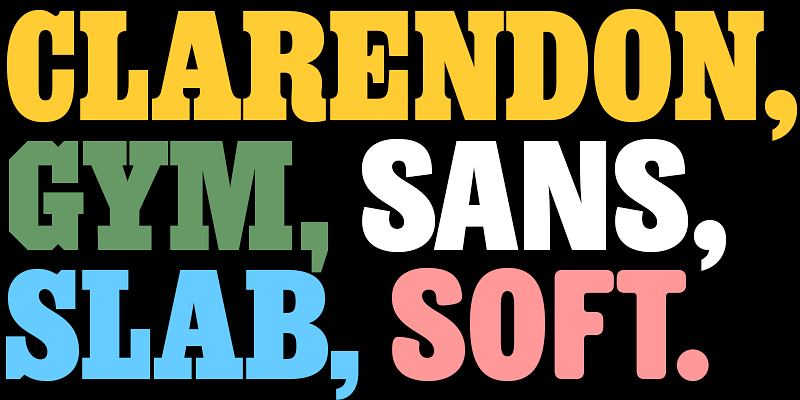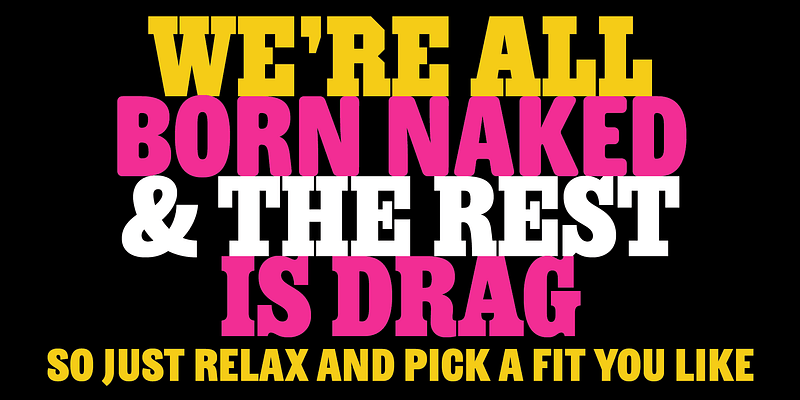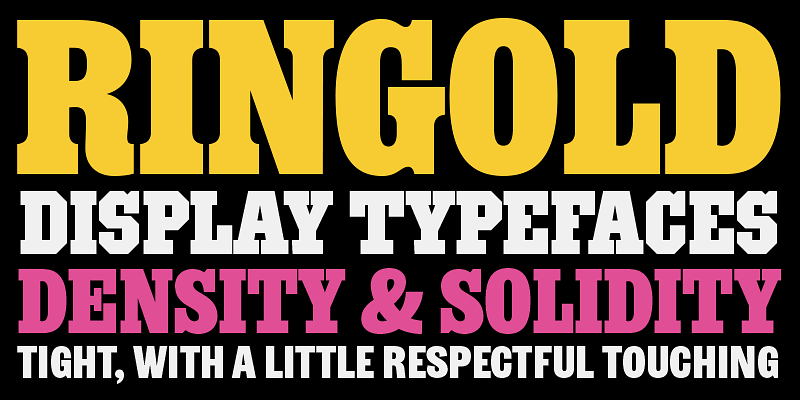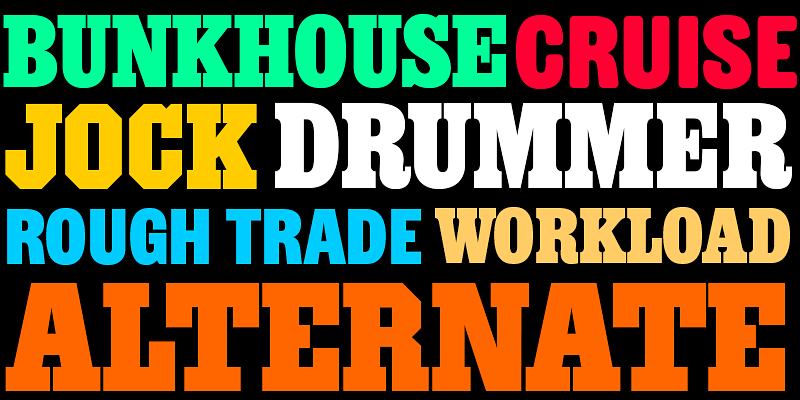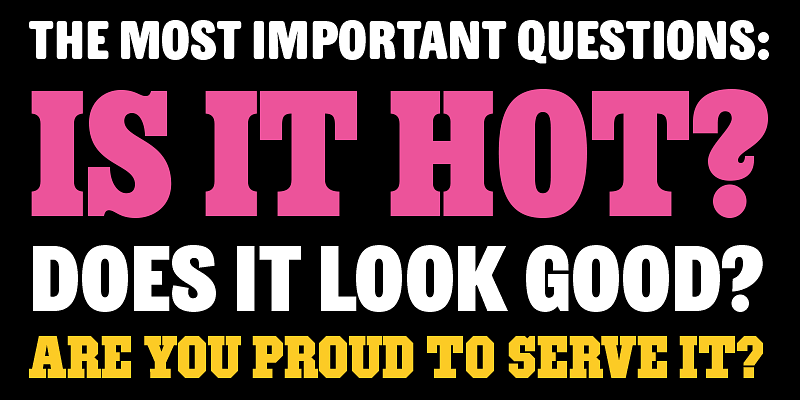
Ringold est idéale pour les gros titres accrocheurs, dont les lettres doivent être serrées mais sans se toucher. Ajustez le ton de votre texte grâce aux variantes de cette famille qui partagent les mêmes proportions et la même densité, mais dont la personnalité évolue d’un style à l’autre. Ringold Clarendon est un peu fantaisiste et nostalgique. Sa cousine Ringold Slab est plus austère et sérieuse. Ringold Gym donne du muscle à la version Slab et la rend plus architecturale. Ringold Sans enlève les empattements mais conserve une certaine chaleur. Ringold Soft est une version plus douce et plus conviviale de la version Sans. Ces cinq styles prennent en charge environ 505 langues chacun.